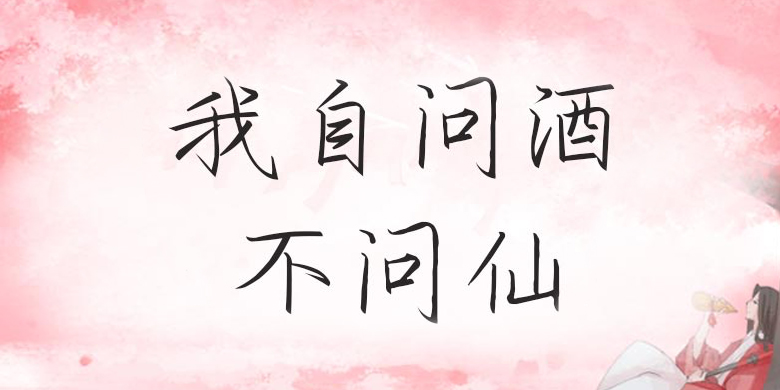
方正手迹-我自问酒不问仙
方正手迹-我自问酒不问仙,这款字体结构工整、笔画清晰,兼顾美观与易读性,适用于标题、正文、海报、包装、LOGO 等多种场景。字形优雅稳定,风格百搭耐看,适配日常排版与创意设计,让文字呈现更舒适、更具质感。方正手迹-我自问酒不问仙一笔一画,皆是细节,以均衡的比例、流畅的线条打造舒适视觉体验,字形端正大气,风格简约现代。无论是商业设计、品牌宣传还是日常排版,都能轻松驾驭,让文字更有格调与力量。方正手迹-我自问酒不问仙字体下载。
我自问酒不问仙是一款充满优雅气质的手写体。该字体整体中宫收紧外围笔画延伸舒展,内紧外送。所以适用于文艺类的书刊、品牌广告和产品包装设计,以及社交网络的个性化用字。